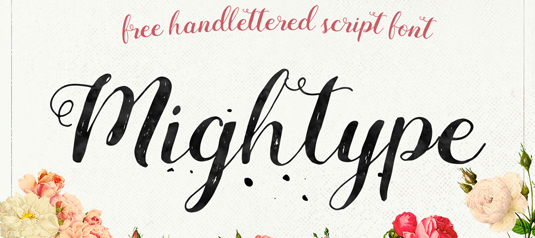
47 font chữ viết tay miễn phí tuyệt vời
Những font chữ viết tay đang dần trở nên phổ biến hơn bao giờ hết. Và đây là 47 font chữ viết tay tuyệt vời mà bạn hoàn toàn có thể download miễn phí.
Nếu bạn cần một font chữ viết tay cho dự án của mình, hãy tìm ở ngay bài viết này. Khi chúng ta nói về những font chữ viết tay, chúng ta không chỉ đang đề cập đến một phong cách của typography; mà là một kiểu chữ cần rất nhiều kỹ năng. Nó cũng là một dạng font chữ viết thảo nhưng ít gò bó hơn và dựa vào những đường nét tự do.
Gần đây, phong cách typography này xuất hiện nhiều hơn bao giờ hết, được ưa thích hơn trong in ấn cũng như trong kỹ thuật số so với các font truyền thống. Dưới đây là top font chữ miễn phí mang phong cách viết tay mà bạn có thể sẽ thích và download chúng đấy. Hãy cùng RGB.vn tham khảo nha.
01. Yunus
Font Yunus được tạo ra bởi graphic designer Faraz Ahmad. “Mỗi một chữ cái đã được nắn nót rất cẩn thận để làm câu chữ của bạn trông thật đẹp,” tâm sự của tác giả trên Behance. Kiểu chữ này được tạo nên từ rất nhiều yếu tố, khiến nó phù hợp với tất cả các phong cách của những dự án sáng tạo.
02. Cavorting
“Đây chính là font chữ một-ngày,” Missy Meyer – người sáng tạo ra kiểu chữ Cavorting này nói. “Tôi đã tạo ra mẫu chữ và thực hiện tất cả những việc như canh khoảng cách giữa các ký tự và các nhóm chữ chỉ trong vòng một ngày.” Và như Meyer nói, kiểu chữ viết tay ‘goofy’ này có thể được sử dụng cho cả mục đích cá nhân và thương mại.
03. Mightype
Miễn phí cho mục đích cá nhân và thương mại, Mightype đã được tạo ra bởi một nhóm tại AF Studio. Là một font chữ viết tay, Mightype là lựa chọn tuyệt vời cho việc thiết kế bao bì, xây dựng thương hiệu và hơn thế nữa.
04. Futuracha
Hãy thêm vào một chút thanh lịch cho thiết kế của bạn với font viết tay Futuracha tuyệt đẹp này.
Một nhóm những designer tò mò chuyên khám phá đã lập nên nhóm holy và đó cũng chính là nhóm thiết kế đứng sau font viết tay Futuracha tuyệt đẹp này. Trang The holy trên Behance nói rằng: “Cái tên là sự kết hợp của từ future (tương lai) và cucaracha (nghĩa là con gián trong tiếng Tây Ban Nha). “Thiết kế này dựa trên font Futura book cơ bản. Cạnh chữ được mở rộng ra một cách hoàn toàn khác biệt để gợi nhắc đến phong cách Art deco.”
05. Reis
Thiết kế viết tay Reis được tạo ra bởi Marcelo Reis Melo. Là một font tuyệt vời cho poster, logo và hơn thế, Reis miễn phí cho mục đích cá nhân và thương mại, và dĩ nhiên, sự đóng góp này của tác giả, luôn đáng được trân trọng.
06. Bellaboo
Cần một font viết tay độc quyền cho dự án mới nhất? Bellaboo của Marcelo Reis Melo có thể chính là những gì bạn đang tìm kiếm. Là một thiết kế táo bạo, Bellaboo rất tuyệt cho việc tạo ra các tiêu đề bắt mắt, poster.
07. Ludicrous
Là một font viết tay miễn phí khác của Missy Meyer, Ludicrous rất tuyệt trong việc gợi ra cảm giác viết tay chân thật. Miễn phí cho cả mục đích cá nhân và thương mại, sự đóng góp của tác giả là rất đáng trân trọng.
08. Fofer
Fofer được tạo ra bởi nhà sáng lập của Mousse Creative và giám đốc sáng tạo Angie Raess. “Đôi khi những dự án tốt nhất lại được tạo ra từ những khó khăn,” Raess viết trên Behance. “Chúng tôi cần một font chữ đặc biệt nhưng không thể tìm thấy. Còn cách nào tốt hơn việc sử dụng chính chữ viết tay của mình?” Fofer có thể được download trên Behance, tất cả những gì Raess cần trả lại chỉ là một cái tweet đơn giản mà thôi.
09. California Sans
California Sans là một font viết tay, được tạo ra bởi designer gốc Mexico Noe Araujo. Được miễn phí download, thiết kế này bao gồm bộ đầy đủ các chữ cái viết hoa và thường, chữ số và vô số ký tự đặc biệt.
10. Ruffle Beauty
Nếu bạn đang tìm một font viết tay tinh nghịch, giải pháp lần này chính là Ruffle Beauty của Anis Iday. Rất lý tưởng cho các thiết kế poster, Ruffle Beauty miễn phí cho cả mục đích cá nhân và thương mại.
11. Skinny
Đến nay, font viết tay này là thiết kế phổ biến nhất trên mạng của artist được biết đến với tên notfon1234. Bản update cuối cùng của thiết kế đã được gọt giũa lại khoảng cách và nét chữ, và hiện tại font chữ này hoàn toàn miễn phí cho mục đích thương mại.
12. Gunny Rewritten
Dựa trên font Gunny Handwriting cũ, type designer Vit Condak cho ra một font viết tay miễn phí mới, đó là Gunny Rewritten. Không hài lòng với phiên bản gốc, Condak đã hoàn toàn tạo dựng lại thiết kế này và giờ đây nó được download miễn phí cho tất cả những ai cảm thấy thích thú.
13. Halo Handletter
Font viết tay thanh nhã này được phát triển bởi graphic designer Mario Arturo. Là một trong hơn 20 font chữ được thiết kế bởi Arturo, người chuyên về các font chữ viết tay bay bướm, Halo Handletter chính là một ví dụ hoàn hảo sau cùng. Font chỉ được sử dụng miễn phí cho mục đích phi thương mại.
14. LeHand
LeHand là font chữ đầu tiên được tạo ra bởi indieferdie. Font LeHand phản ánh phong cách viết tay tinh nghịch, điều sẽ khiến các dự án thiết kế mới của bạn trở nên tuyệt vời hơn. Là một web designer và branding designer, chúng tôi nghĩ rằng indieferdie sẽ còn có nhiều những công việc truyền cảm hứng phía trước hơn nữa.
15. Yore
Được tạo ra bởi designer Việt Nam Poem haiku, Yore mang đến nhiều niềm vui hơn so với các font viết tay truyền thống. Bị ảnh hưởng từ các hình ảnh minh họa, Yore là một font hoàn hảo cho những thử nghiệm nội dung mới và thậm chí sẽ thể hiện rất tốt trên các dự án xây dựng thương hiệu.
Bạn sẽ phải trả $5 cho designer khi sử dụng nó với mục đích thương mại.
Font viết tay miễn phí ‘Whatever it takes’quay ngược trở lại kiểu typography phấn và bảng. Đây là font miễn phí khi sử dụng cho mục đích cá nhân và phi lợi nhuận. Tuy nhiên bạn sẽ phải quyên góp $5 cho bất kì mục đích thương mại nào, dĩ nhiên là nó vẫn rất đáng giá.
17. Before Breakfast
Gần đây, designer SimonStratford khám phá ra app iFontMaker trên iPad chỉ ngay sau khi được thách thức tạo ra một font chữ với nó trong vòng chưa tới 10 phút. Kết quả ư? Chính là kiểu chữ vẽ tay Before Breakfast này đây. Có thể đó không phải là một trong những font miễn phí được quan tâm nhất trong danh sách ở đây, nhưng, như những gì Stratford nói: “Đó là một niềm vui, kiểu chữ viết tay này đã phá vỡ những quy luật trong typography.”
18. Engine
Là một trong những font viết tay miễn phí ưa thích của chúng tôi, thiết kế này của Fedie Balderas bao gồm các chữ cái viết thường và in nghiêng cũng như viết hoa và viết thường. Tác giả thậm chí hỗ trợ nhiều ngôn ngữ khác như tiếng Pháp, Tây Ban Nha và Ba Lan cho font chữ này.
19. Chomp
Chomp là một thiết kế ngộ nghĩnh của designer gốc Camberwell William Bayley Suckling. Là một sinh viên ở The London College of Communication, Suckling thường thử nghiệm các font chữ khác nhau và rất vui vẻ cho phép bạn sử dụng nó với bất kỳ mục đích cá nhân hay thương mại nào.
20. LSTK Bembo
LSTK Bembo được truyền cảm hứng từ một font chữ trong những quyển sách cũ.
Là một trong những font viết tay miễn phí dễ thương nhất mà chúng tôi đã tìm kiếm từ rất lâu, LSTK Bembo là một bài thơ ca ngợi dành cho tổ tiên của kiểu chữ in sách, đó là Bembo. Phiên bản vẽ tay của kiểu chữ cổ điển này có thể được sử dụng bất cứ khi nào bạn cần sự kết hợp giữa cá tính, truyền thống và một chút quan điểm riêng. Font postscript này bao gồm nhiều yếu tố quan trọng tạo nên ngoại trừ chữ x thường.
21. Haiku’s Script
Font viết tay miễn phí Haiku’s Script là sự thử nghiệm đầu tiên của Poem Haiku trong việc sáng tạo ra một kiểu chữ mới. Được bắt đầu từ năm 2011 và mất 3 tháng để hoàn thành, từ tháng 7 đến tháng 9. Font chữ này miễn phí đối với việc sử dụng cho mục đích cá nhân và Poem Haiku sẽ rất vui khi được nghe bất cứ ý kiến hay bình luận nào về font chữ này.
22. Pops
Một designer gốc New York Sune Matres tự đưa ra một nhiệm vụ cho bản thân đó là tạo ra font chữ dựa trên một trong các cách viết tay của cha anh ấy – một người rất đặc biệt – font chữ này thường được sử dụng trong các thông điệp ngắn và tiêu đề. Chúng tôi cực kỳ thích thú khi đưa mẫu thiết kế kỳ diệu này vào danh sách những font chữ viết tay miễn phí này.
23. Sketch Block
Font tiêu đề phác thảo tay này được thiết kế bởi artist Lukas Bischoff. Tác giả nói rằng: “Được tạo ra độc quyền từ phác thảo tay của chính tôi và sau đó được số hóa, Sketch Block là một font hoàn hảo cho việc sáng tạo ra các cá tính nhân vật, hoặc minh họa hình ảnh bằng typography.” Chỉ miễn phí cho mục đích cá nhân, đây là một trong những font viết tay miễn phí đẹp nhất mà chúng tôi từng được nhìn thấy từ rất lâu.
24. GoodDog
Hãy kết hợp font chữ trang trí mềm mại này của Fonthead Design vào các dự án cá nhân của bạn.
Một font chữ trang trí hiện đại, GoodDog được tạo ra bởi Fonthead Design. Kiểu chữ cong này là một lựa chọn phổ biến với gần 1 triệu lượt tải về từ khi được ra mắt. Font viết tay miễn phí này đã được hoàn chỉnh với toàn bộ chữ cái viết thường, in hoa, chữ số và ký hiệu.
25. J.D Handcrafted
J.D Handcrafted là một trong 16 font chữ được tạo ra bởi Emerald City Fontwerks, thiết kế thời thượng này đang trở thành một trong những font phổ biến nhất của studio. Kiểu chữ viết tay chải chuốt này miễn phí sử dụng cho mục đích cá nhân với đầy đủ các ký tự tùy ý bạn sử dụng.
26. Amatic
Một thiết kế súc tích, tỉ mỉ và kỳ quặc của typographer Vernon Adams, font viết tay miễn phí này phù hợp một cách hoàn hảo với các thiết kế vui nhộn, ví dụ như truyện tranh hài ngắn. Amatic chỉ có các chữ in hoa nhưng bao gồm cả cách viết thường và in đậm.
27. Journal
Được tạo ra bởi Hans Gerhard Meier hay còn gọi Fontourist, tên của font chữ tay tuyệt đẹp này giải thích chính xác loại thiết kế mà nó phù hợp. Đây là một trong 3 font được thiết kế bởi Meier và là font chữ được download phổ biến nhất đến nay của tác giả.
28. Mari & David
Font viết tay miễn phí quyến rũ này được thiết kế bởi designer/typographer người Chile Rodrigo German. Font Mari & David bao gồm chữ thường, in đậm, và siêu đậm, có nghĩa là có rất nhiều thứ để “nghịch” với font chữ này đấy. Font chữ này cũng bao gồm luôn cả các chữ số và ký hiệu khi bạn download.
29. Daniel
Daniel là một trong rất nhiều font được tạo ra bởi designer Danial Midgley. Miễn phí khi dùng cho cả mục đích cá nhân và thương mại, Daniel bao gồm bộ đầy đủ chữ in hoa, viết thường, chữ số và nhiều ký tự đặc biệt.
30. Sumitra
Font viết tay dựa trên lối viết hoa mỹ này được tạo ra bởi graphic designer và typographer gốc Nepal Ananda Maharjan. Đặt font chữ này lên một nền màu nước khiến cho tính linh hoạt của nó trở nên rất nổi bật.
31. LSTK Clarendon
Được tạo ra bởi một mobile studio ở Áo – Elastik, đây là font chữ miễn phí thứ hai của họ được ra mắt với mọi người. Họ mô tả nó như một “phiên bản viết tay siêu ngầu của kiểu chữ slab serif trong tiếng Anh, đó là Clarendon”, với lời lý giải cho cái tên. Font chữ bao gồm cả kiểu in đậm và viền nét.
Font viết tay miễn phí này – Mawns’ Handwriting – được tạo ra bởi Måns Grebäck - graphic designer chuyên về thiết kế font chữ, logo và typography. Mawns’ Handwriting được sử dụng miễn phí cho mục đích cá nhân, và dĩ nhiên một khoản quyên góp dành cho tác giả thì luôn được khuyến khích.
33. Bispo Nova
Jackson đã tạo ra font Bispo sau khi được học về nghệ thuật viết chữ calligraphy trong vài tháng.
Bispo là một kiểu chữ viết tay được lấy cảm hứng từ nghệ thuật viết chữ nghiêng cổ, với một ngòi bút bi dẹt và một ngòi bút cỡ số 10. Thiết kế bởi typographer người Brazil Jackson Alves, anh quyết định cho phép tất cả mọi người sử dụng để có thể tạo ra các tác phẩm với nghệ thuật viết chữ quyến rũ và tận dụng được các tính năng của định dạng Opentype
Font viết tay miễn phí này tạo hiệu ứng phấn bảng tuyệt vời cho thiết kế của bạn.
Chúng tôi đã phải tìm một font viết tay phong cách phấn bảng miễn phí vào danh sách này và đây chính là một sự lựa chọn hoàn hảo được thiết kế bởi Alphabeta85. Nó bao gồm cả chữ viết in, viết thường, cũng như chữ số, dấu chấm câu và ký hiệu. Cũng như thường lệ, hãy đảm bảo là bạn chỉ dùng nó cho mục đích cá nhân thôi nhé!
35. Linny
Font chữ siêu dễ thương này được thiết kế bởi Maya hay còn gọi là Linny. Kiểu viết tay này thật ra chính là chữ viết tay của Maya, và sau khi được đề nghị để phát triển nó thành một font cho mọi người sử dụng, cô ấy đã đồng ý! Font chữ bao gồm cả viết in, viết thường cũng như chữ số và dấu câu.
36. Fatstack
Hãy sử dụng font chữ có sức nặng này cho những thiết kế thật táo bạo.
Chúng tôi yêu font chữ mạnh mẽ này, một font chữ nguyệch ngoạc thân thiện thiết kể bởi Blambot Comic Fonts and Lettering. Bao gồm toàn bộ các chữ cái viết in, đây là một font viết tay miễn phí hoàn hảo dành cho những tác phẩm thiết kế thật sự táo bạo. Gói miễn phí cũng sẽ được bao gồm các dấu câu và chữ số.
37. Soft Sugar
Font viết tay vui nhộn này chỉ được download miễn phí ở định dạng thường nhưng chúng tôi nghĩ nó cũng là một font tuyệt vời để “nghịch” đấy. Gợi lên cảm giác về những font chữ truyện tranh truyền thống, chúng tôi chắc rằng bạn sẽ có thể tạo ra những điều thật đặc biệt với nó.
Được truyền cảm hứng từ những đường tỉ lệ trong kiến trúc, font viết tay vuông vắn gọn gàng này được tạo ra bởi Kimberly Geswein. Là tác giả của hơn 200 font chữ, Geswein thường cho phép nhiều thiết kế, bao gồm cả font chữ này, được miễn phí sử dụng cho mục đích cá nhân.
Là một trong 82 kiểu chữ được phát triển bởi Gem Fonts, Worstveld Sling Extra chính là một trong những thiết kế viết tay nổi tiếng nhất, nhận được hơn 400 ngàn lượt download từ khi ra mắt. Miễn phí sử dụng cho mục đích cá nhân, gia đình font viết tay miễn phí này bao gồm bộ đầy đủ chữ in, chữ thường, chữ số và nhiều ký tự đặc biệt.
40. Housegrind
Font viết tay siêu ngầu này được sáng tạo bởi graphic designer Måns Grebäck, chuyên gia về thiết kế logo và typography. Chỉ miễn phí sử dụng cho mục đích cá nhân, nên khi muốn có giấy phép thương mại cho Housegrind bạn có thể mua nó thông qua website Aring Typeface.
41. VersionType
Là một font condensed sans-serif, VersionType được tạo ra bởi designer lão luyện Victor Coreas. “Nó được thiết kế để trở nên thật tinh nghịch và phóng khoáng,” tác giả nói. Kiểu chữ bao gồm bộ đầy đủ chữ in, chữ thường, chữ số, ký tự đặc biệt, và dĩ nhiên nó miễn phí sử dụng cho mục đích cá nhân và phi lợi nhuận.
42. Billy
Billy là font chữ được ra đời từ chính chữ viết tay của tác giả. “Vì là chữ của chính tôi nên cũng không mất nhiều thời gian để tạo ra nó,” Claire nói, “Vậy nên tôi quyết định tải nó lên để mọi người có thể tự do sử dụng!”
Font chữ miễn phí cho mục đích cá nhân và phi lợi nhuận sử dụng (mặc dù dĩ nhiên sẽ rất tốt nếu như có thêm một sự ghi nhận hoặc lời cám ơn); nếu bạn muốn dùng nó cho mục đích thương mại, hãy liên lạc với Claire.
43. Novito Nova
Novito Nova được tạo ra bởi designer người Nga Nina Z. “Font này được tạo ra để làm mọi người thật vui vẻ,” Nina bình luận trên Behance. Là một thiết kế lạ thường, Novito Nova rất tuyệt trong việc tạo nên một cảm giác viết tay chân thực cho dự án của bạn.
44. Mink Type
Mink Type được tạo ra bởi art director gốc New York Filiz Sahin. “Mink Type là một kiểu chữ vẽ tay rất ngầu được phát triển bằng cách sử dụng công cụ brush trong Illustrator,” cô ấy nói. “Mỗi chữ cái bao gồm định dạng in hoa, viết thường để bạn có thể tạo ra cảm giác linh hoạt cho thiết kế của mình.”
45. Happy Fox
Tất cả những gì Caldentey và Llull cần để bạn có thể download miễn phí đó là một cái tweet đơn giản.
Thiết kế của font chữ Happy Fox là sự cộng tác giữa illustrator Laura Caldentey và Fran Llull. Với mong muốn đem đến một font chữ mảnh khảnh cho dự án của họ, Caldentey đã vẽ ra một hệ thống chữ cái và những yếu tố chọn lọc, cô làm việc cũng Llull để khiến font chữ trở nên tinh tế hơn và cho ra bản thiết kế cuối cùng.
46. Dickie
Freelance designer David Ellis đã tạo ra font viết tay Dickie bằng cách sử dụng MyscriptFont, một công cụ online cho phép bạn tạo ra font chữ vector từ chính chữ viết tay của bạn. “Đó là một điểm bắt đầu tuyệt vời khi bạn không có nhiều font viết tay để sử dụng, và quy trình khá nhanh,” Ellis nói.
47. Soulmarker
Font chữ viết tay SoulMarker đã được tạo ra bởi nhà thiết kế đồ họa và vẽ tranh minh họa Faraz Ahmad. Font có 2 định dạng: mỏng và đậm, SoulMarker rất thích hợp cho các dự án kỹ thuật số và in ấn.